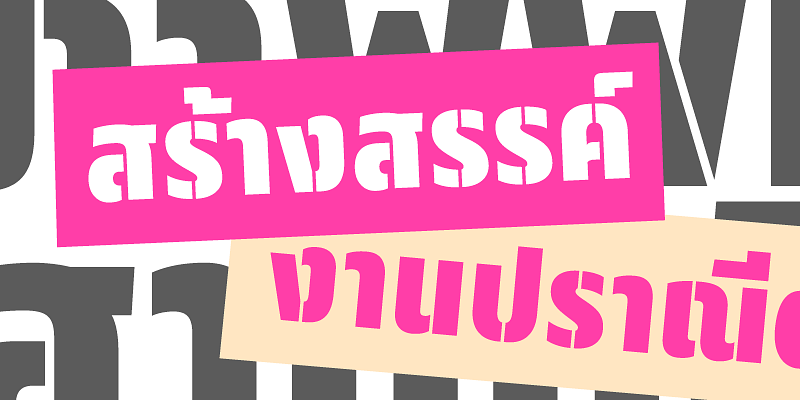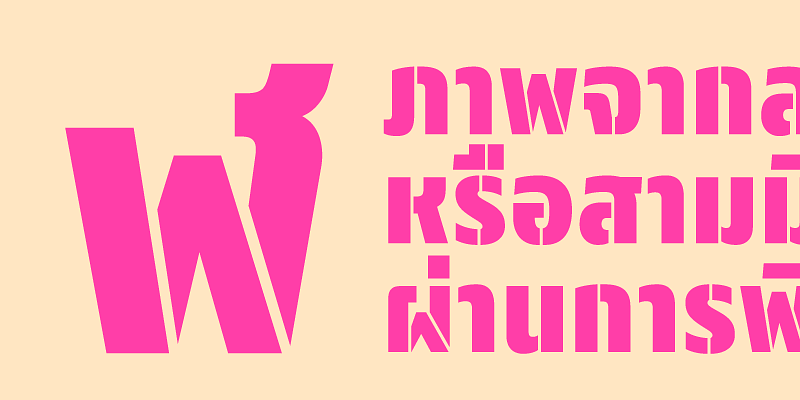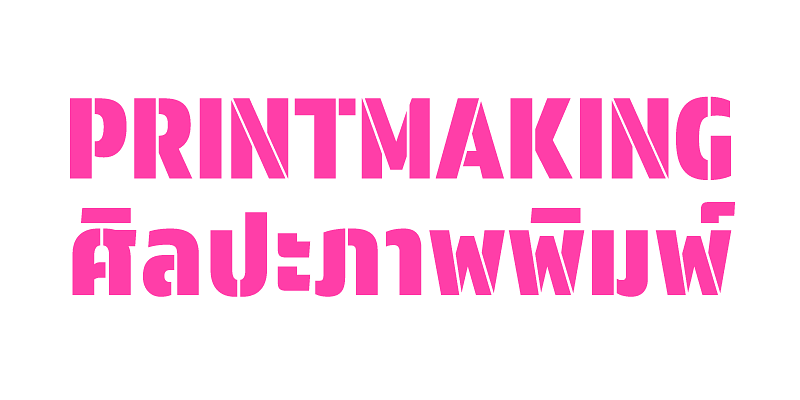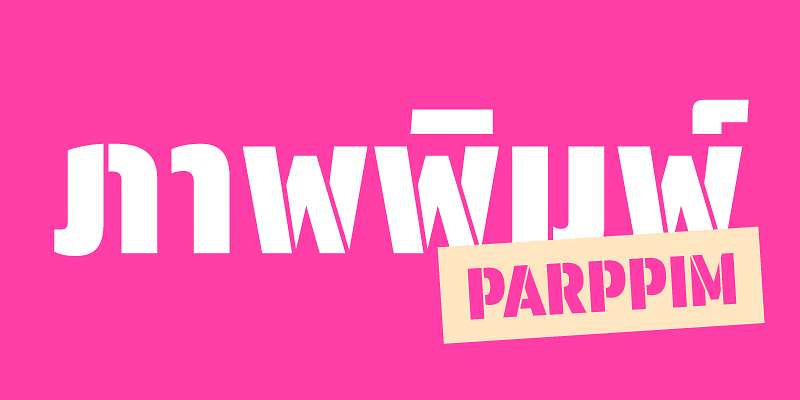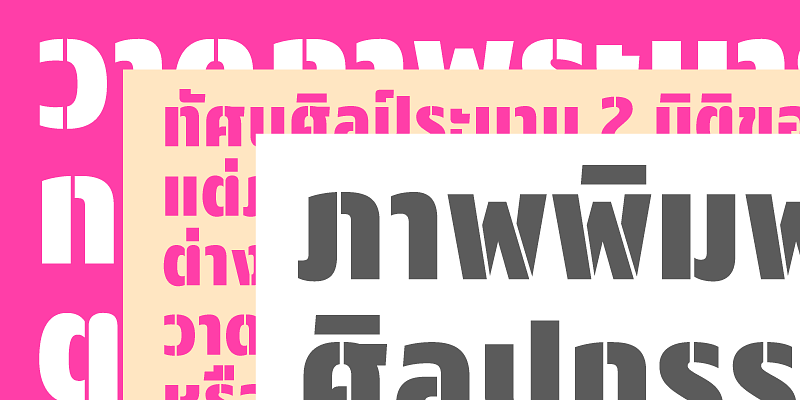
Eine freundliche Sans-Serif-Schablonenschrift mit einem eigenwilligen Stil, der sich in einer kondensierten Form ausdrückt. Parppim eignet sich für die Anzeige, mit einer Reihe von Ligaturen und alternativen Zeichen, die in jedes Layout passen.